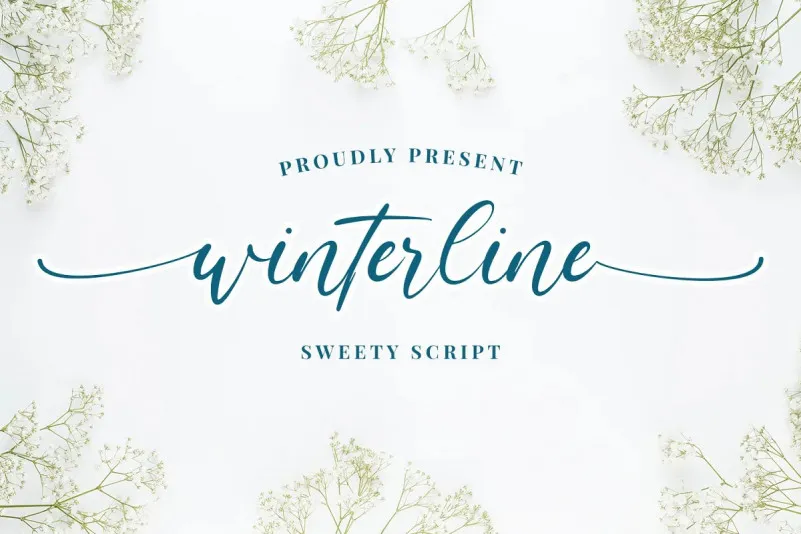
A font Winterline é uma opção perfeita para designers que valorizam a elegância moderna com um toque natural. Esta script font foi criada por Almarkha Type e é parte do catálogo das fontes script disponíveis no 99designs. Com sua aparência casual e encantadora, Winterline traz uma sensação de autenticidade à qualquer design que você desejar desenvolver. É perfeito para projetos como cartões de convite, logomarcas, capas de livros, artefatos artesanais ou qualquer outro tipo de trabalho gráfico. Com sua capacidade única de PUA (Portable User Access), Winterline oferece uma facilidade incrível ao acessar todos os caracteres especiais e sinóticos que ela possui. Além disso, a fonte inclui um leque diversificado de recursos, como alternativas de caracteres e ligaturas, tornando-a ainda mais versátil para uso em diversos projetos. É importante notar que esta é uma versão DEMO da font Winterline, sem todos os seus caracteres, destinada apenas ao uso pessoal. No entanto, toda contribuição é apreciada e bem-vinda pelos criadores desta bela fonte.